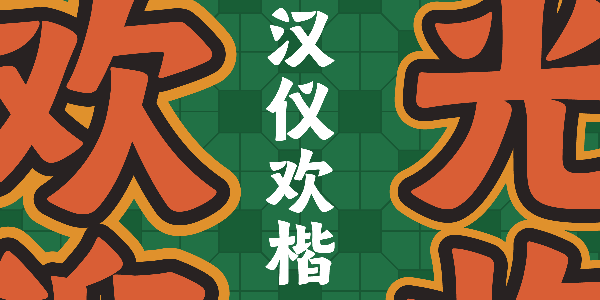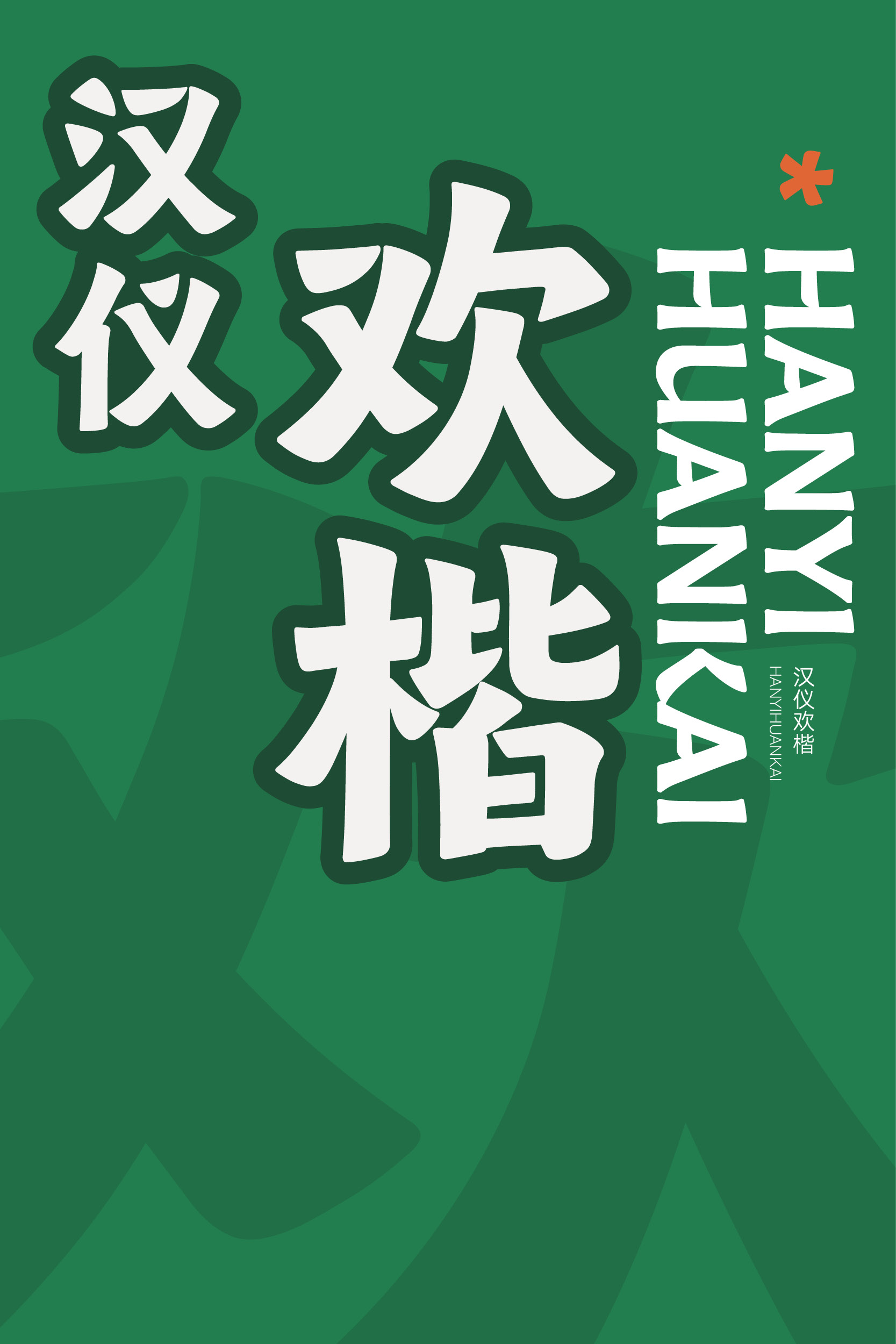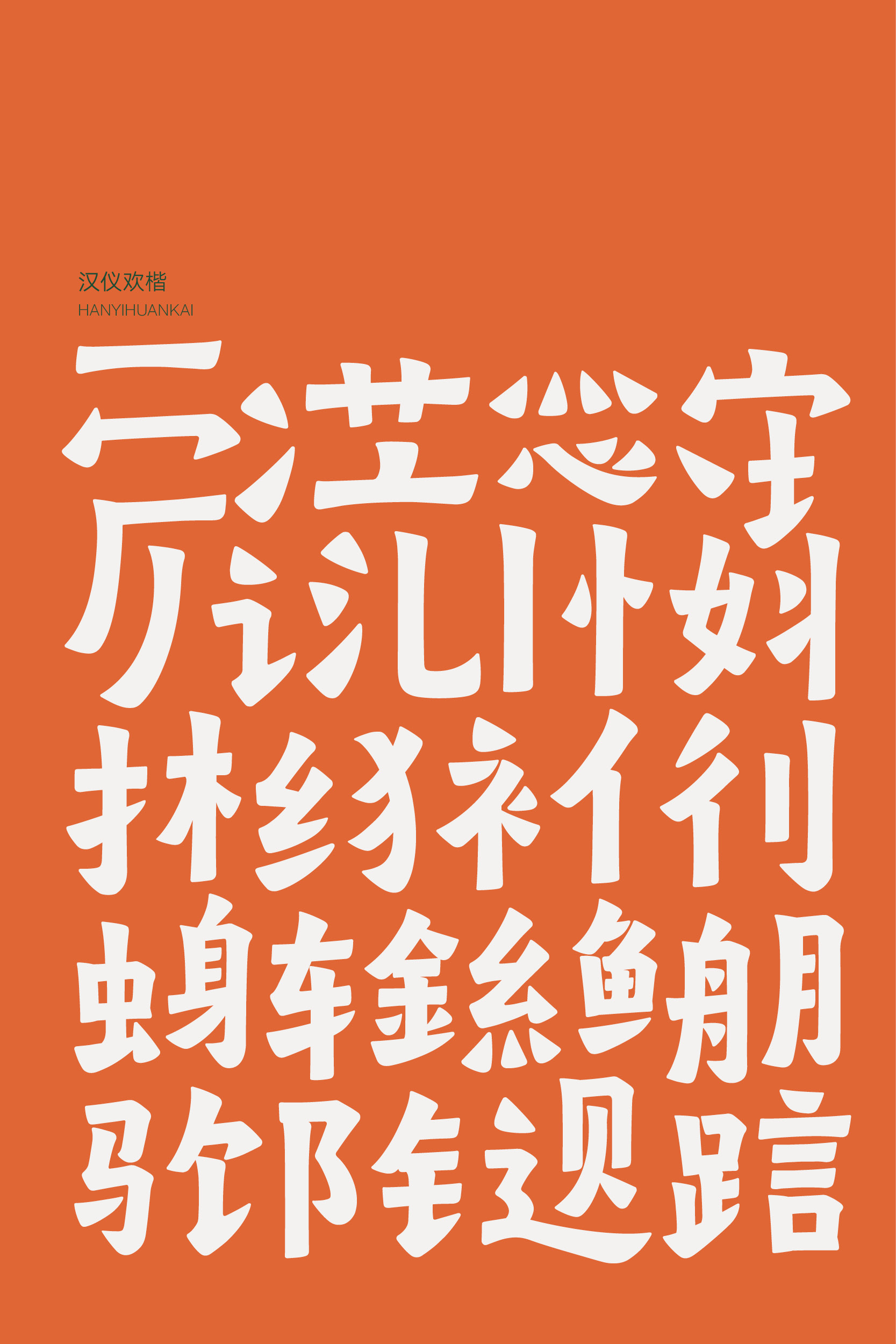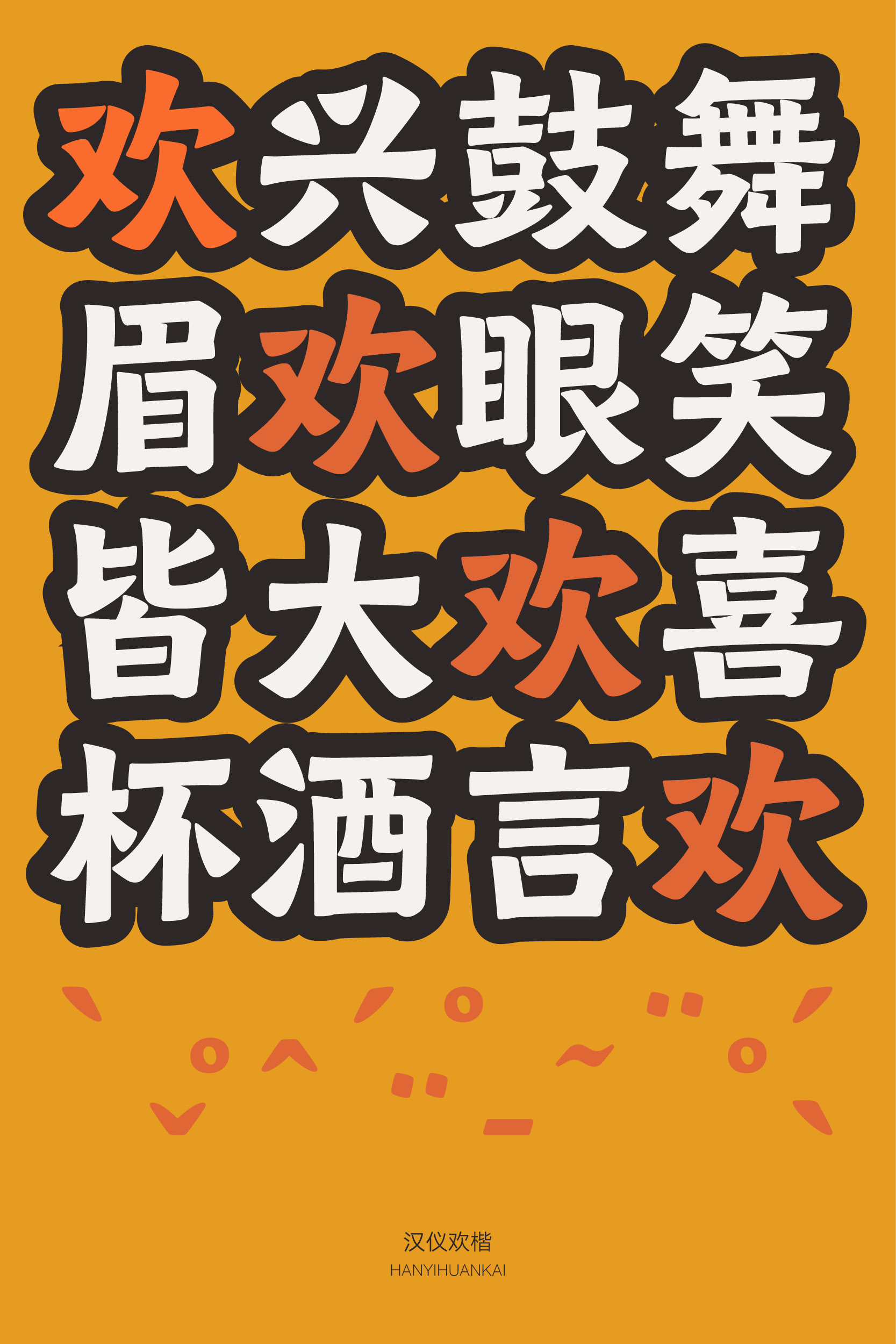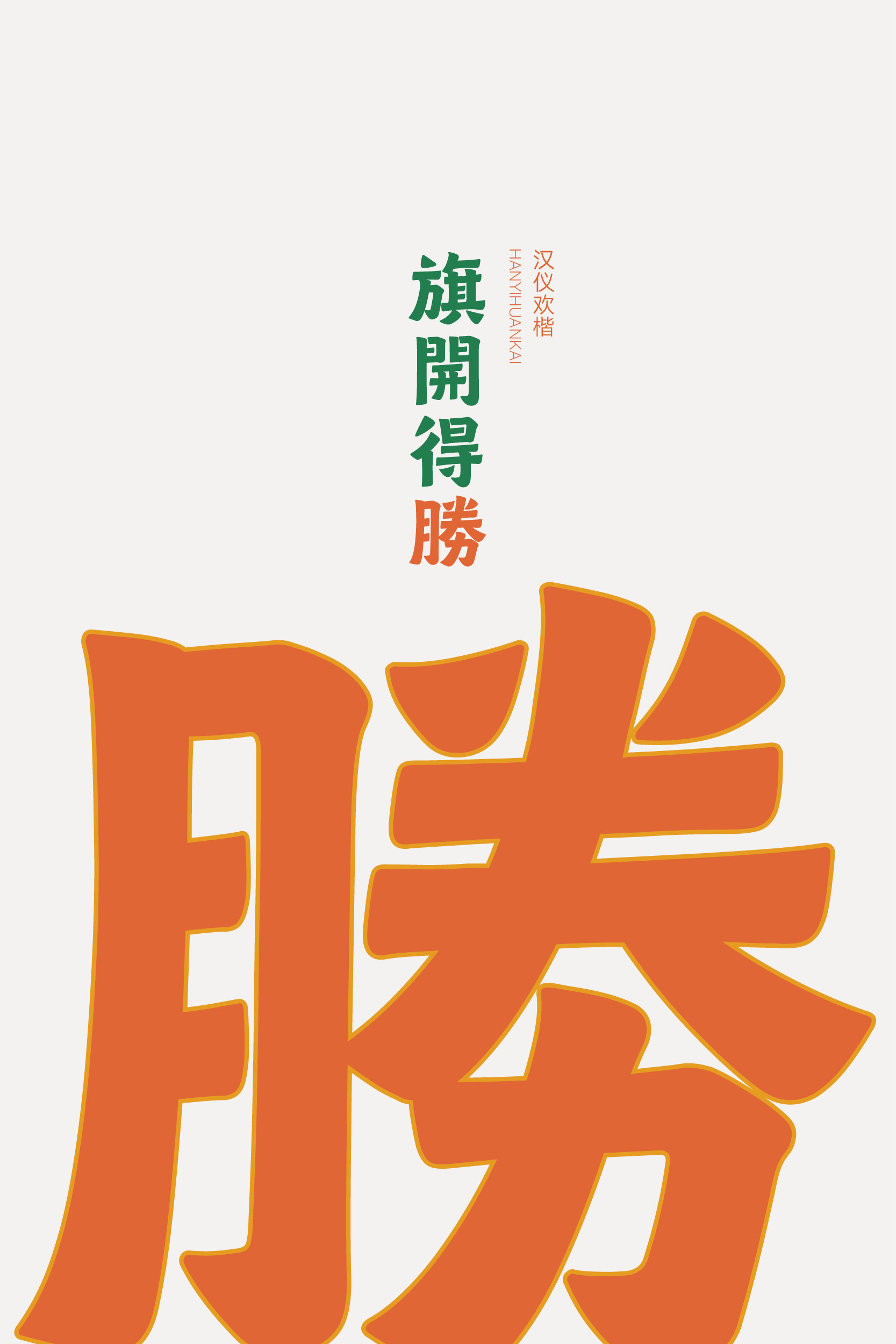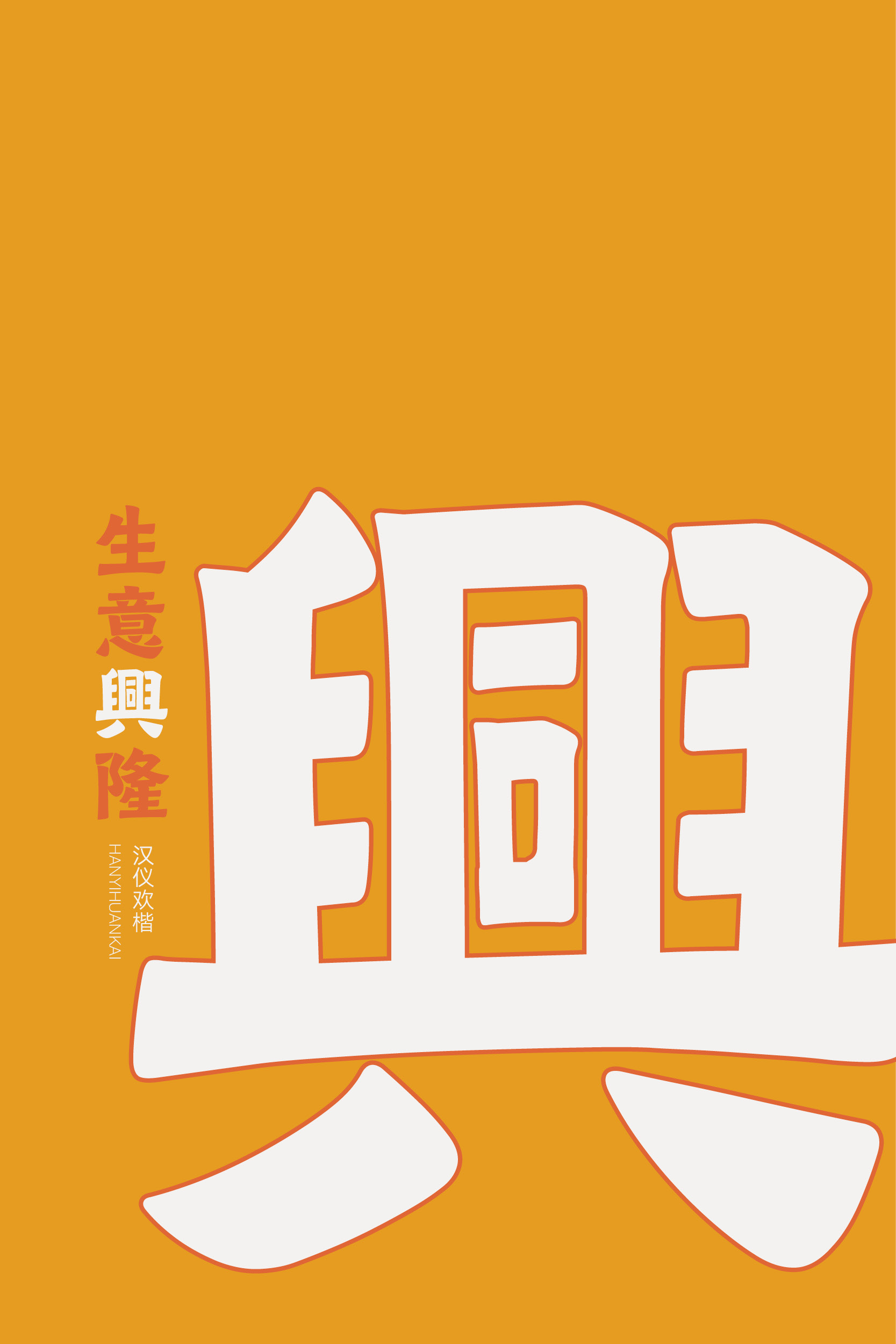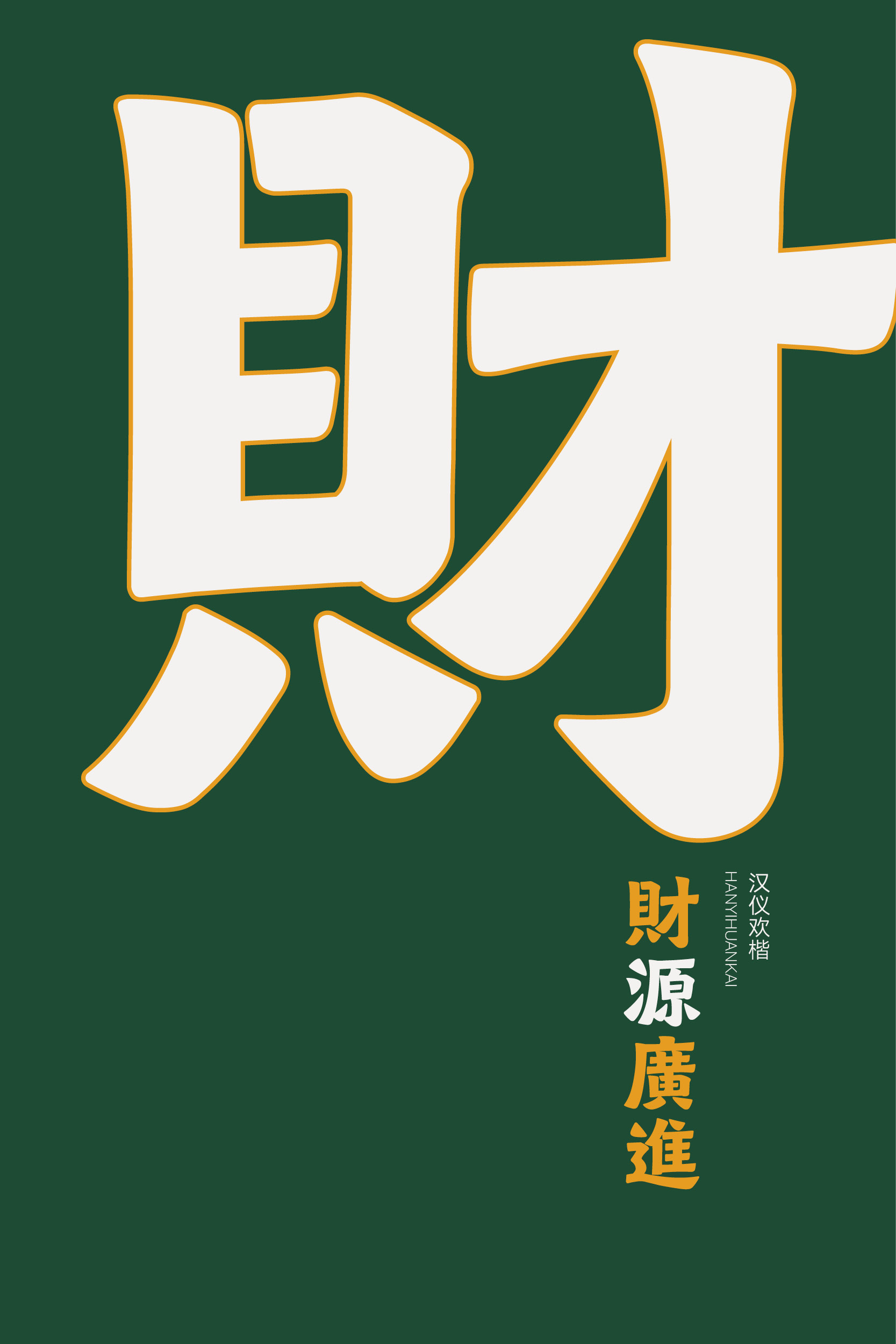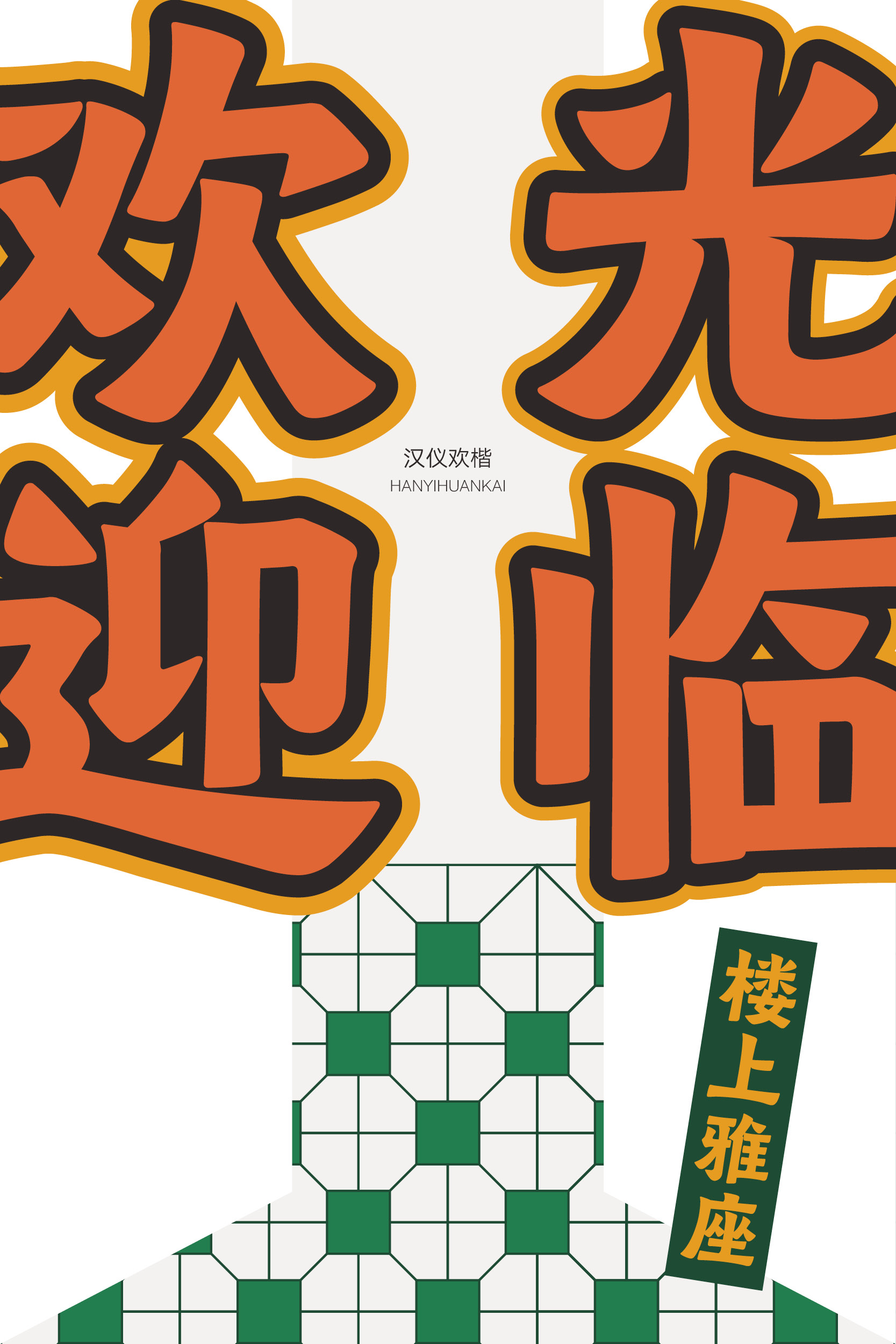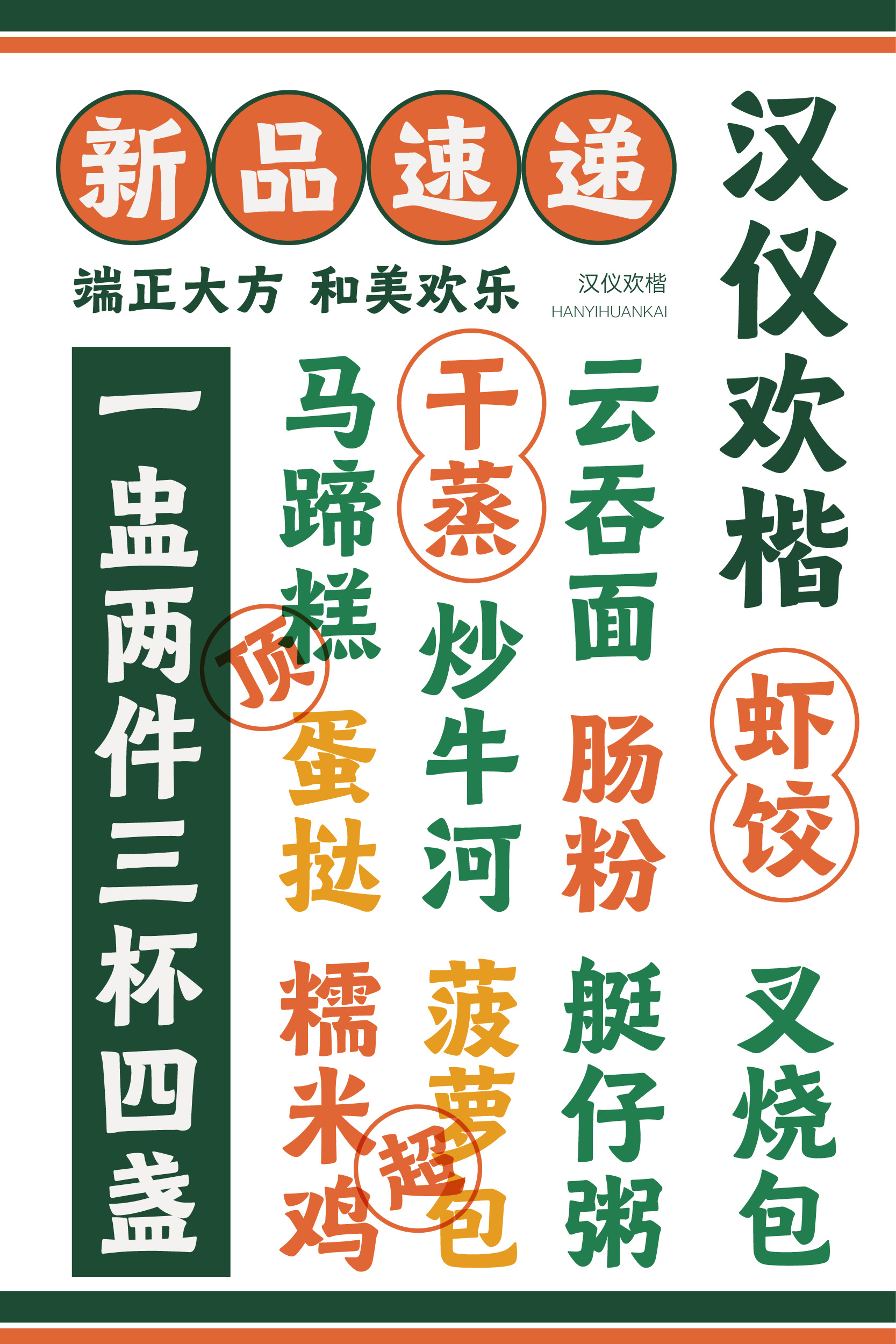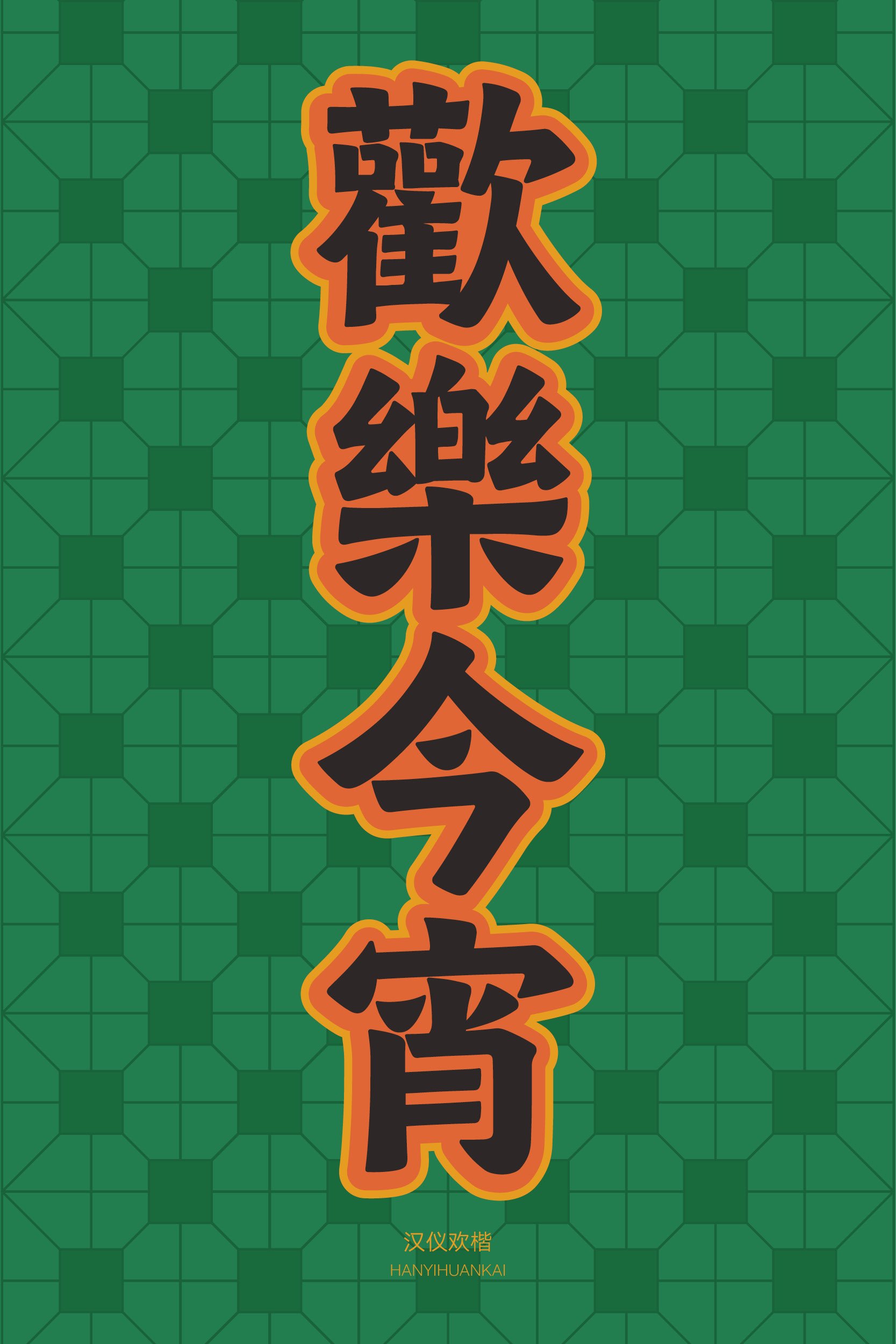
汉仪欢楷
汉仪欢楷,一款具有书写感的设计字体,端正大方之中流露欢喜情绪。取楷书端整平稳的结构,在笔画设计中融入隶书的书写意味,略显隶意的飞扬之势使整体字形多了一分欢喜、雀跃。西文部分同样在平正的造型中融入书写动势,中西文匹配和谐一致。适合用于标题排版或较少字数文本的排版,渲染和美欢乐的氛围。
汉仪欢楷是一款融合隶意的楷书设计字体,既有楷书端正大方的结构,又有隶书的笔意,如微微上扬的嘴角,流露欢喜气质。
点画灵动有势,动静结合,相辅相成。
汉仪欢楷整体气质宽厚质朴,在设计中融入隶书的书写特征。运笔平稳厚实,后接略带隶意的飞扬收笔,使整体字形多了一分欢喜、雀跃。
部分笔画模拟街头喷漆连筋字体的特征,断开的笔画形成独特醒目的效果,更添市井烟火气。
汉仪欢楷的西文部分造型平正之中略有飞扬的动势,融入书写感,与中文部分和谐一致。